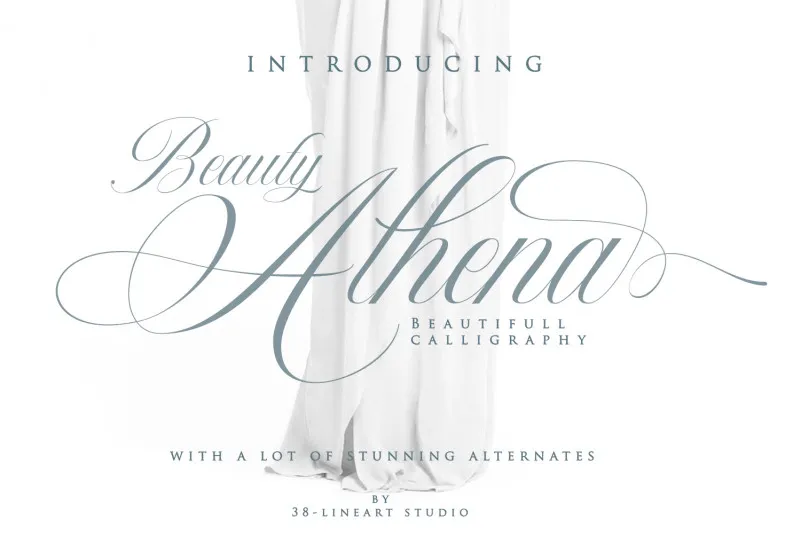
Beauty Athena Font – Download Grátis
Introduzimos a fonte aberta ‘Beauty Athena Font’, uma elegante tipografia caiçara inspirada na divindade grega Atena, conhecida por sua sabedoria, coragem, inspiração e habilidades artísticas. Esta fonte é um prato cheio para quem procura estilos modernos minimalistas ou elegantes expert penmanship. Ela traz conexões entre letras acentuadas, com muitas alternativas de caracteres em várias línguas e números, tudo isso em uma tipografia de cobiça com toque moderno. Uma das características mais interessantes do ‘Athena’ é sua capacidade para criar texturas únicas ao serem combinados. Como resultado, a fonte pode ser utilizada em um vasto espectro de aplicações formais, desde convites até rótulos e embalagens. Ela também se destaca como uma excelente escolha para o design gráfico, moda, literatura, e publicidade. O ‘Athena’ é especialmente apropriado para quem busca elegância sem excesso, clareza na leitura e sofisticação nos detalhes. Se você estiver buscando adicionar um toque de criatividade às suas criações com uma fonte que oferece um resgate visual único, o ‘Athena’ é definitivamente a escolha certa para você.